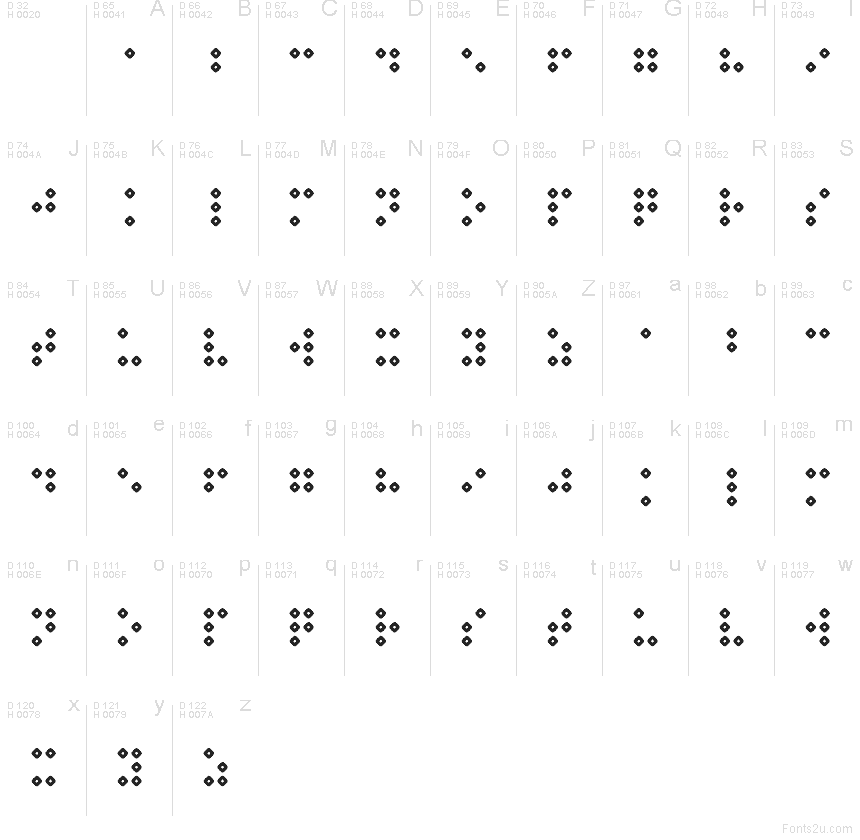
Braillenum Extravagant light
La police Braillenum Extravagant Light de Vladimir Nikolic est une fonte dingbat gratuite inspirée du braille, composée de petits losanges évidés. Les symboles répétés sont disposés dans une grille aérée, conférant à l'ensemble un aspect tactile léger plutôt qu'un bloc dense de points.
Braillenum Extravagant Light est une police gratuite idéale pour des étiquettes tactiles, des visuels autour de l'accessibilité, des bordures, des motifs de remplissage et des séparateurs décoratifs. Son motif de losanges régulier convient parfaitement aux détails d'affiches, au packaging et aux ornements d'interface lorsque vous recherchez une texture évoquant le braille sans utiliser de texte complet.